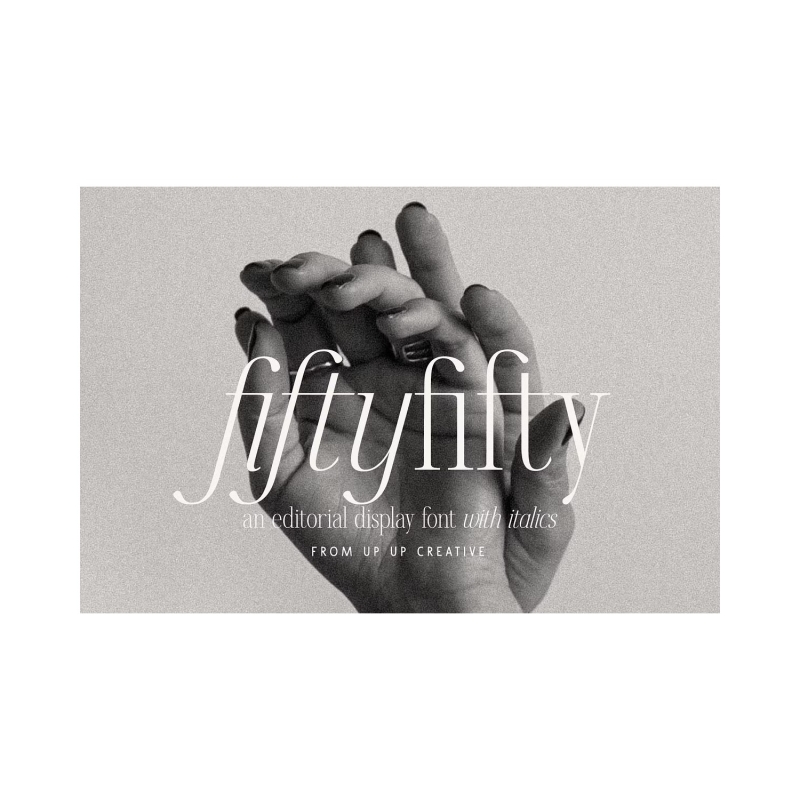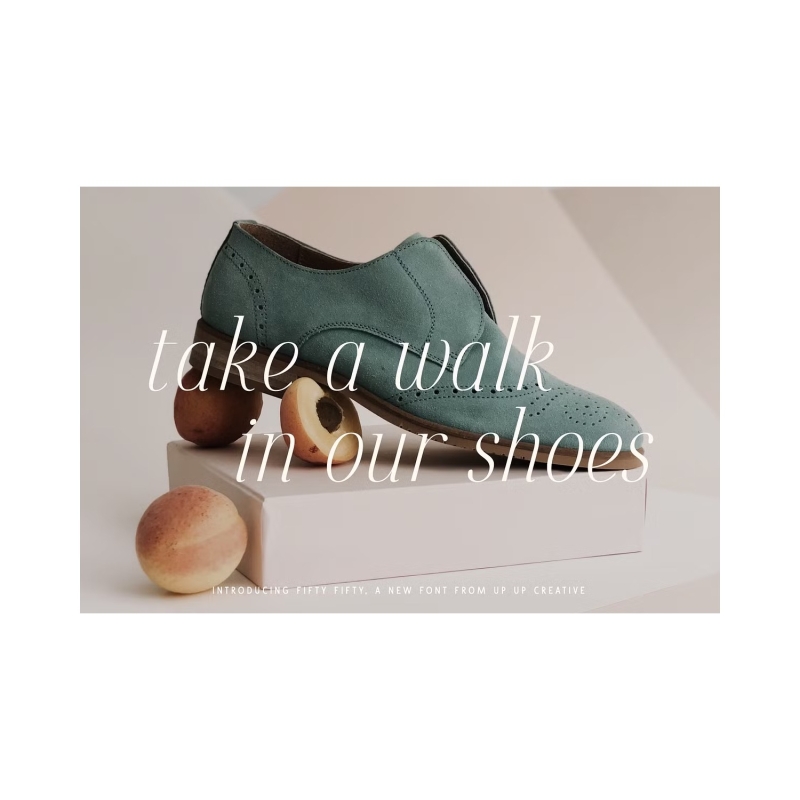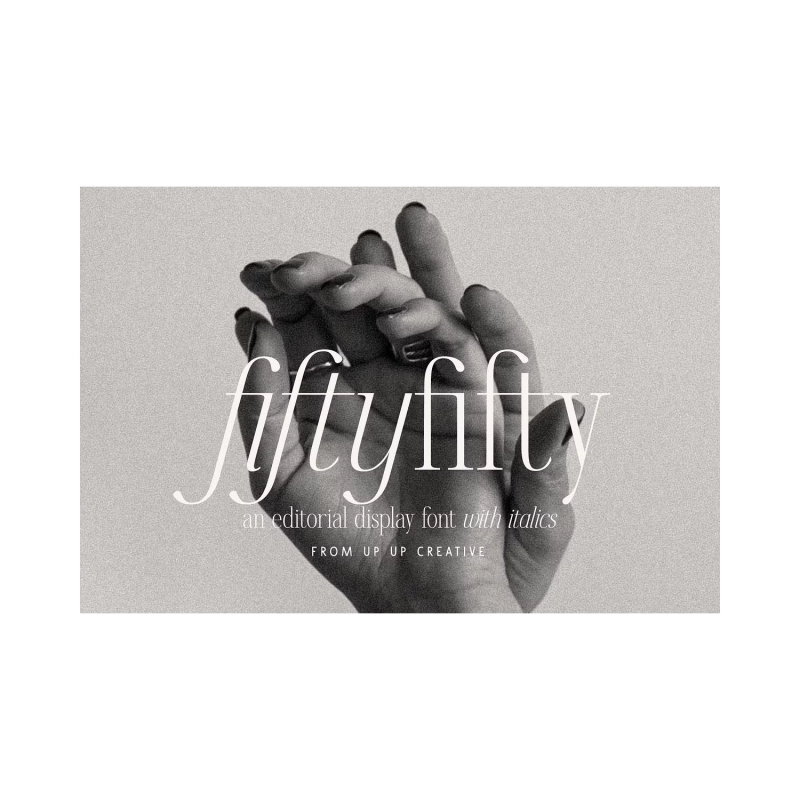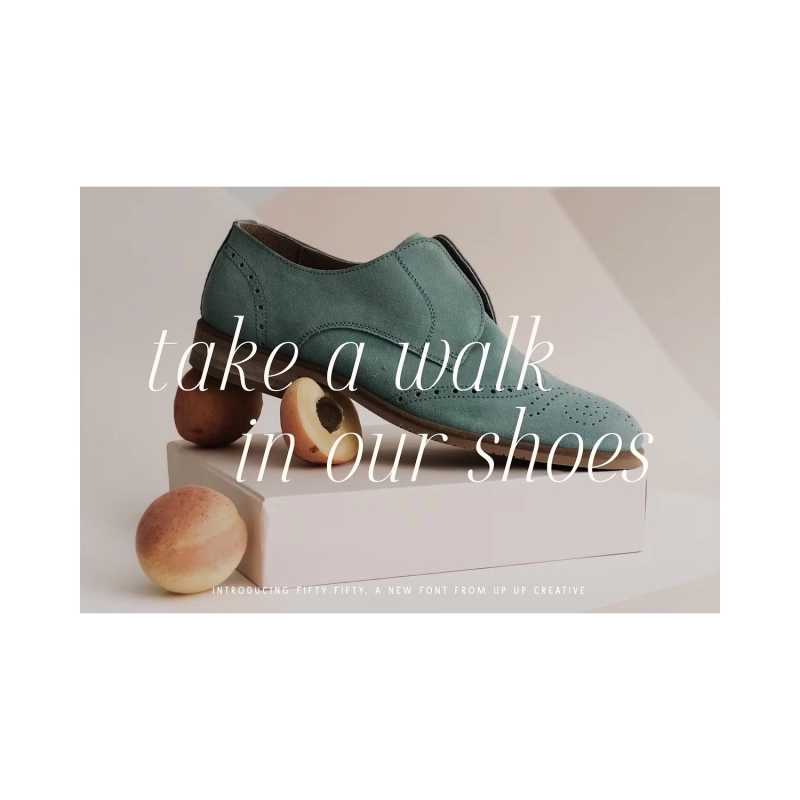
خط فيفتي فيفتي سيريف بخط مائل
Fifty Fifty هو خط serif تحريري (عادي ومائل) مع منحنيات ناعمة وأكثر من 100 حرف مركب. إنه رائع في جميع الأحرف الكبيرة ، لكن الأحرف الصغيرة يمكن أن تحمل أحرف خاصة بها حقا. Fifty Fifty مثالي للعناوين الرئيسية والتصميم التحريري والأحرف والعلامات التجارية والشعارات وتصميم الملصقات والمزيد.
يتضمن Fifty Fifty ما يقرب من 700 صورة رمزية و 115 حرفا مركبا قياسيا وتقديريا. تتضمن ميزات OpenType الإضافية متغيرات الأحرف والمجموعات الأسلوبية والدعم متعدد اللغات (بما في ذلك رموز العملات المتعددة).